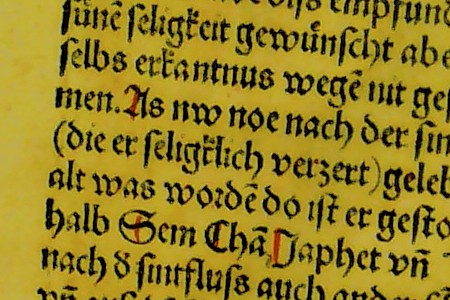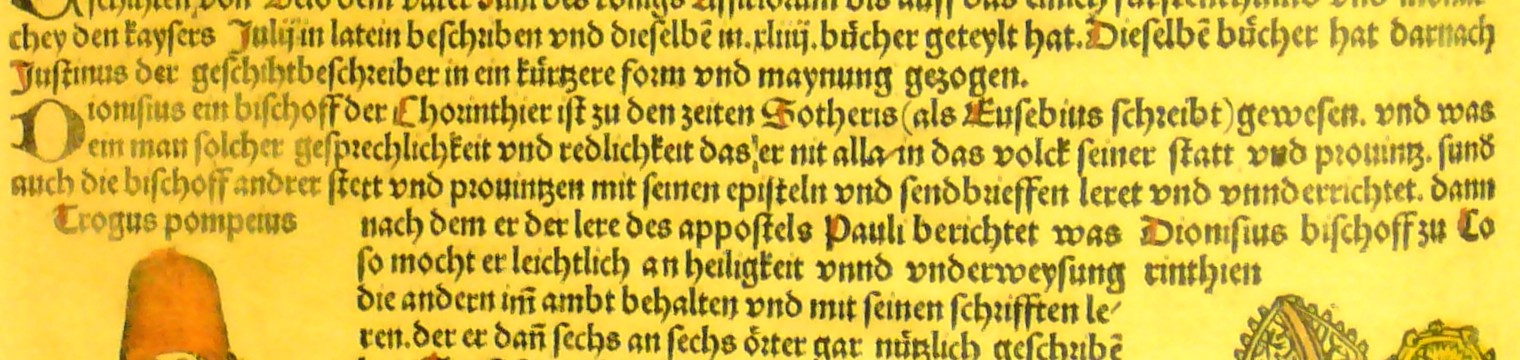
Kann mir jemand schreiben, wann zum ersten Mal in einem nicht-mathematischen Text runde Klammern (als Parenthese) verwendet wurden?
Mein Meyers von 1907 schreibt, dass die Klammern in der Mathematik 1629 eingeführt wurden.
Mir liegt ein literarischer Text vor, gedruckt 1514, der runde Klammern verwendet.
Kennt jemand die Herkunft der Klammern und vielleicht Zeugnisse noch früherer Verwendung?
Ohne Dir ein genaues Datum oder auch nur ein Beispiel nennen nennen zu können, bin ich mir einigermaßen sicher, dass sie mindestens in hoch- und spätmittelalterlichen Handschriften auftauchen.
Hab grad nachgeschaut: die Schedelsche Weltchronik von 1493 (also noch aus der Zeit der Wiegendrucke) enthält die heute gebräuchlichen runden Klammern in uns vertrauter Funktion. Da ja damals im Druck noch eine große Nähe zur Handschrift Angestrebt wurde, ist das ein Indiz dafür, dass sie wahrscheinlich auch um 1450 vor Beginn des Buchdruck-Zeitalters in Gebrauch waren.